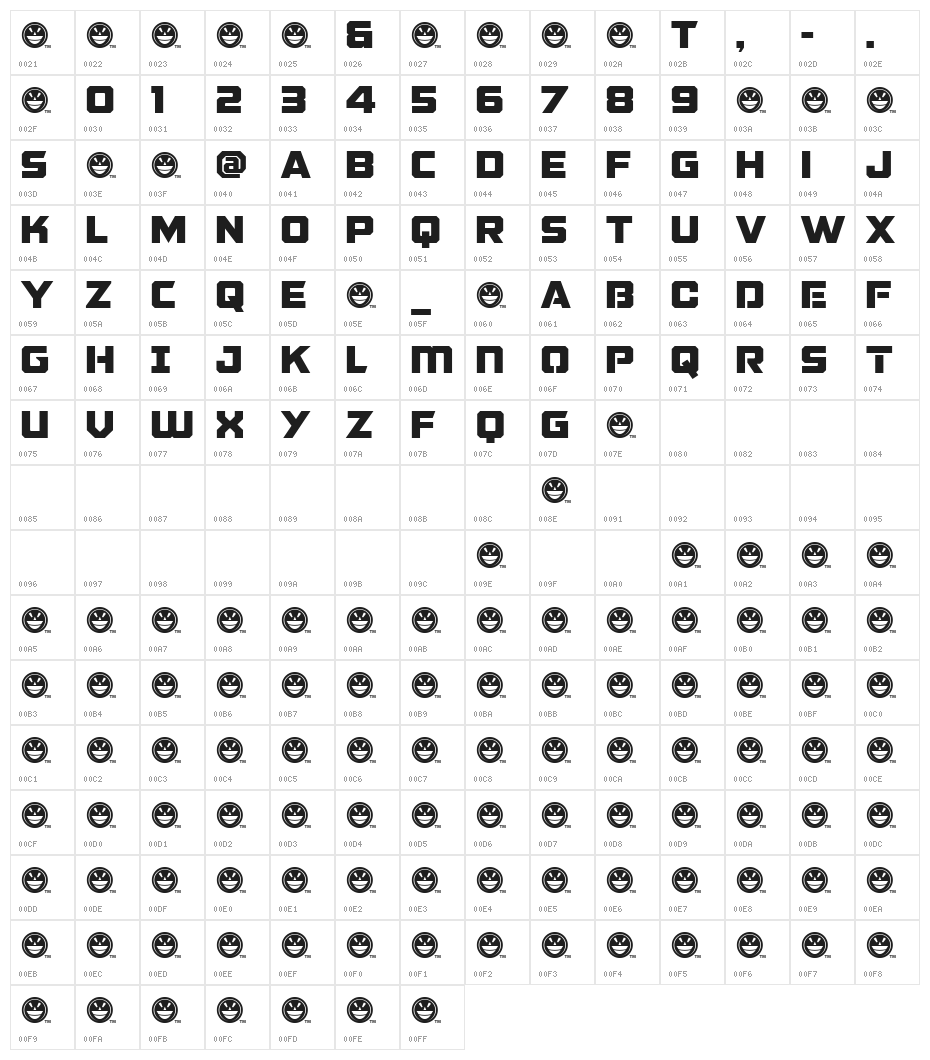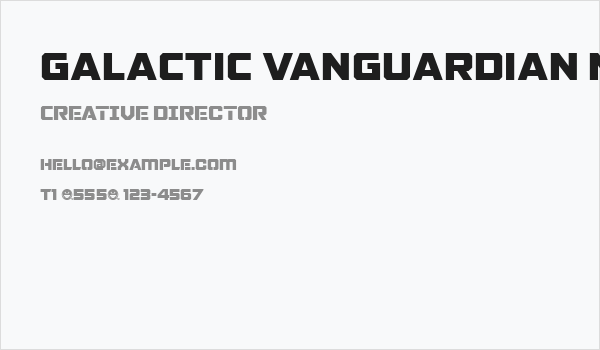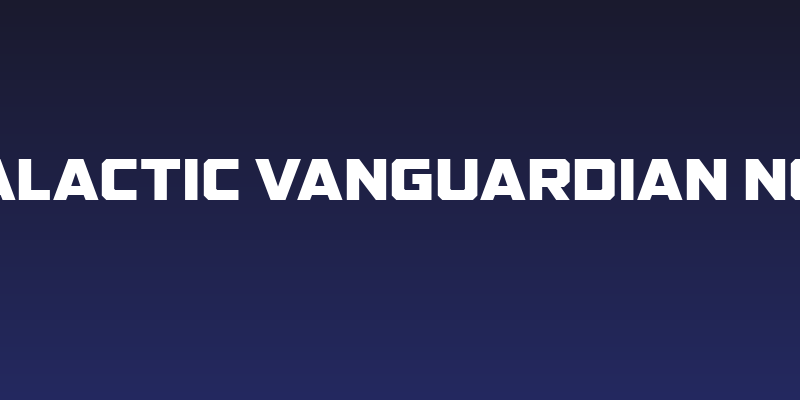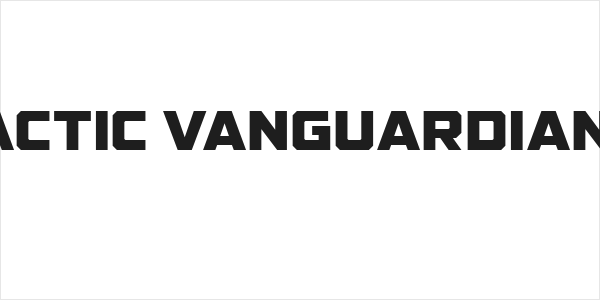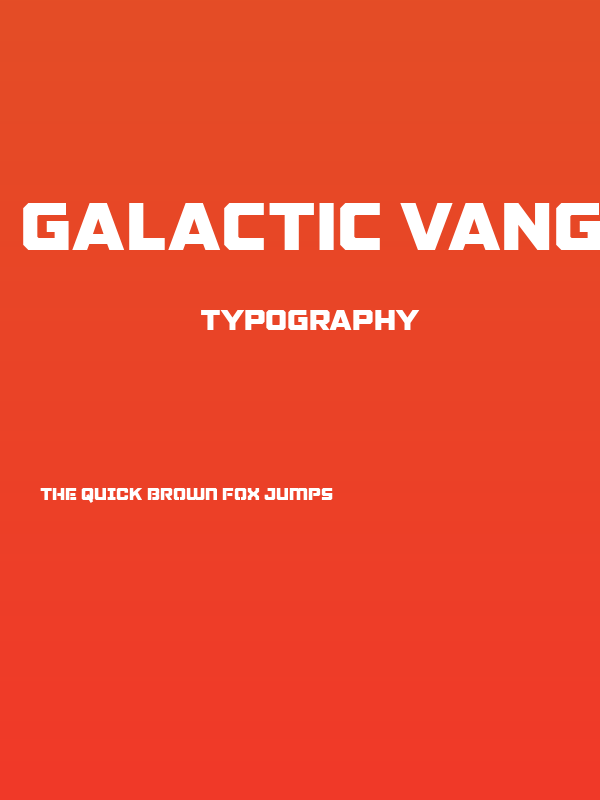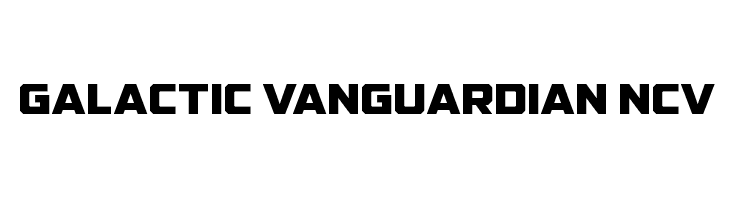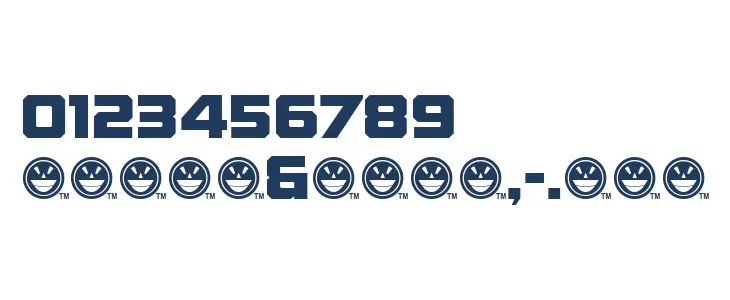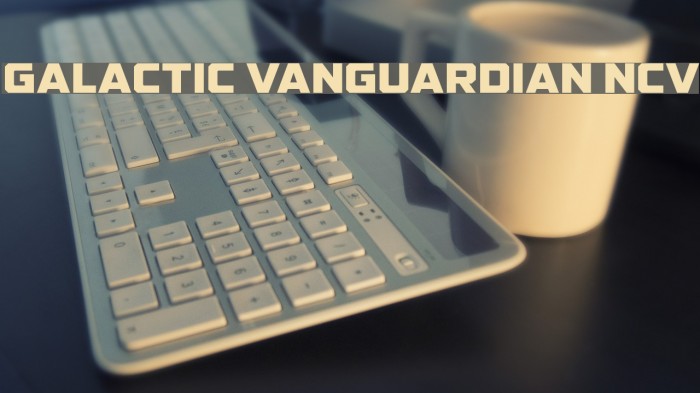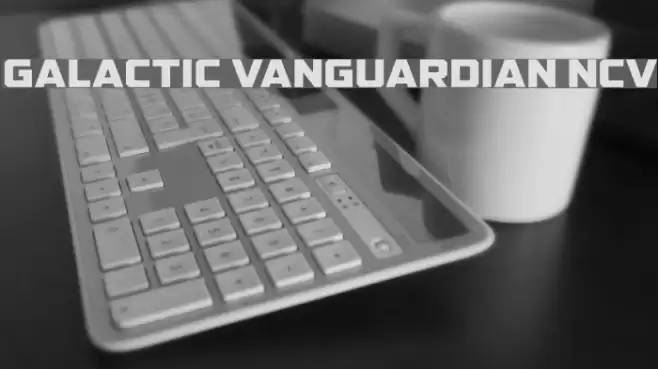
GALACTIC VANGUARDIAN NCV Font
| Projets proposés | Ideal for sci-fi themed designs, video game titles, movie posters, and branding that requires a strong, modern impact. |